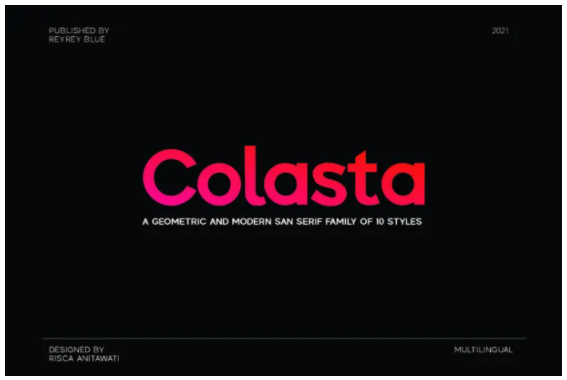
Fontbundles Colasta Font 2021
[Fontbundles] Colasta Font (2021)
Colata - это новое семейство геометрических шрифтов sans-serif, которые привносят свежий, современный вид в любой дизайн. Colata представлена в 10 стилях, каждый из которых содержит малые прописные буквы и глифы для нескольких языков. Этот шрифт очень подходит в качестве текста с отображениями для различных видов брендинга, рекламы, плакатов, баннеров, упаковки, заголовков новостей, журналов, веб-сайтов, дизайна логотипов, баннеров, дизайна социальных сетей и, конечно, вы можете использовать многое другое.